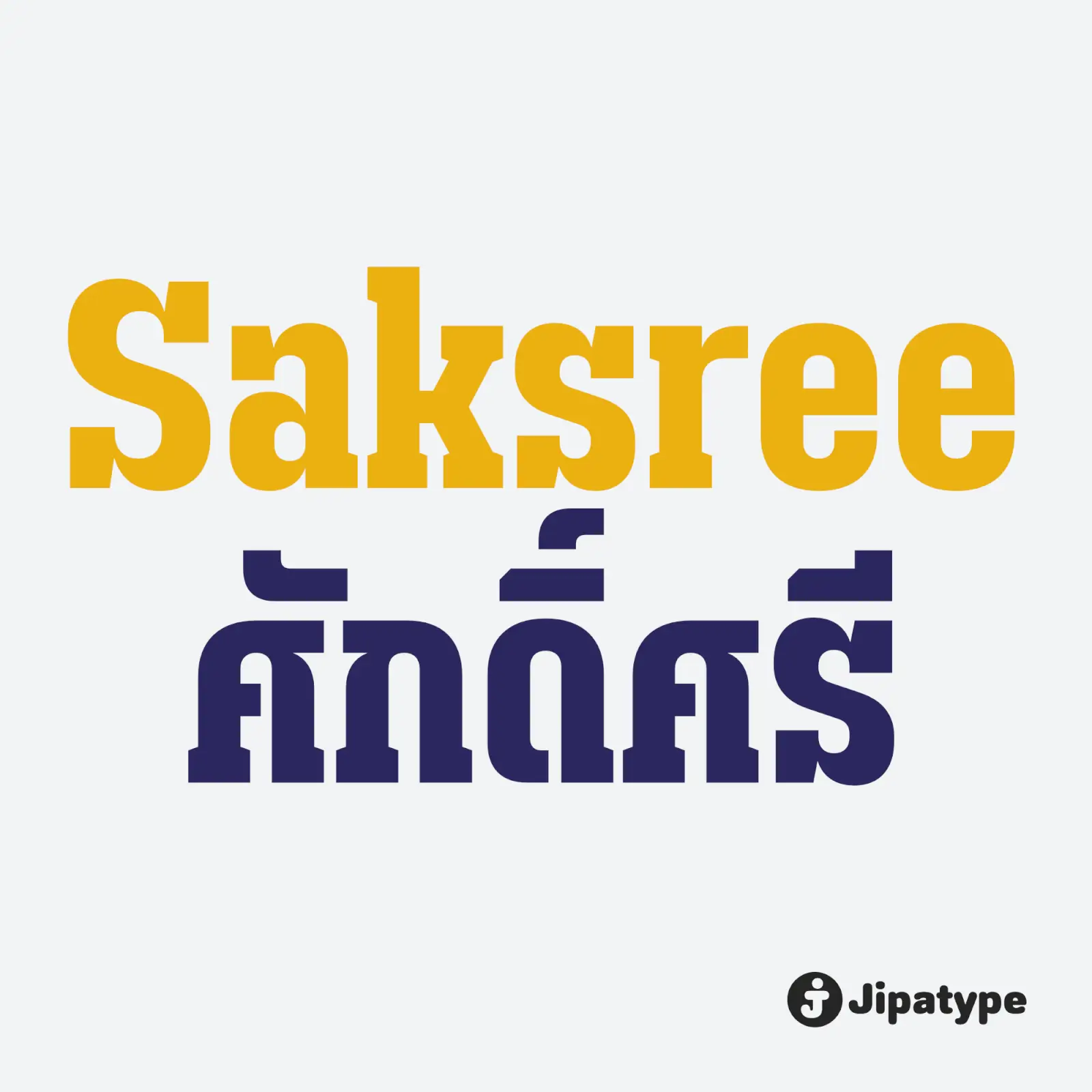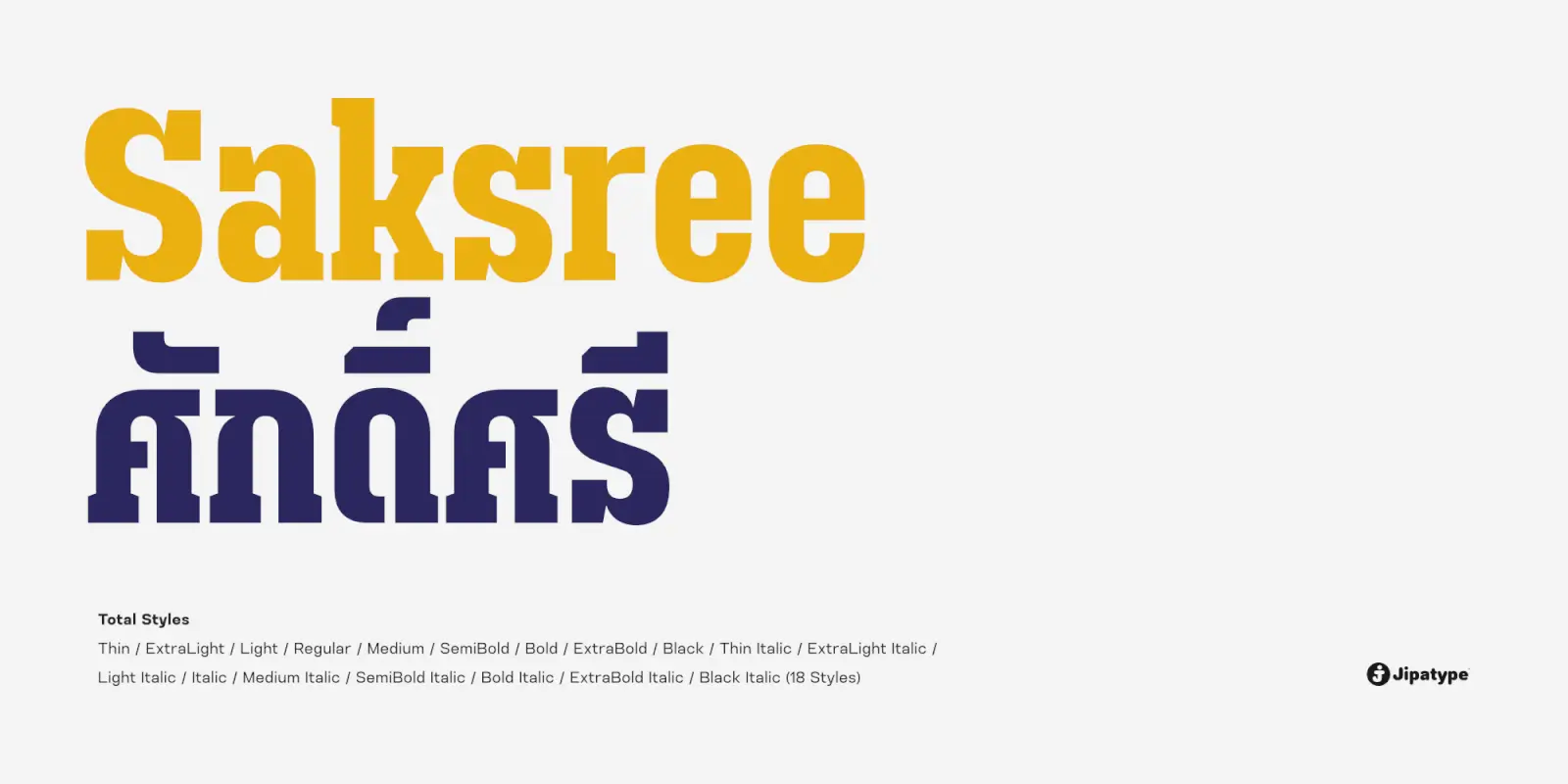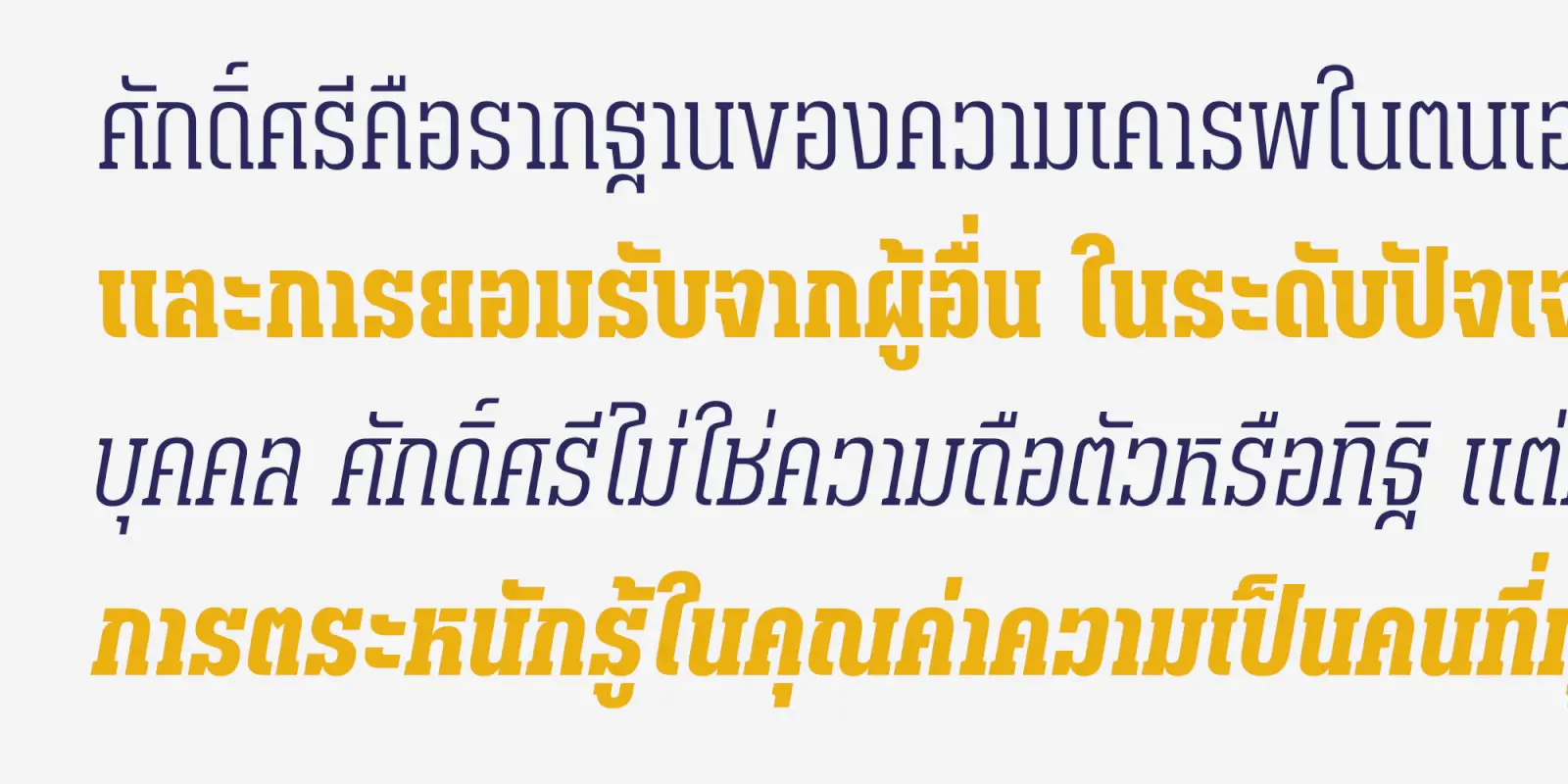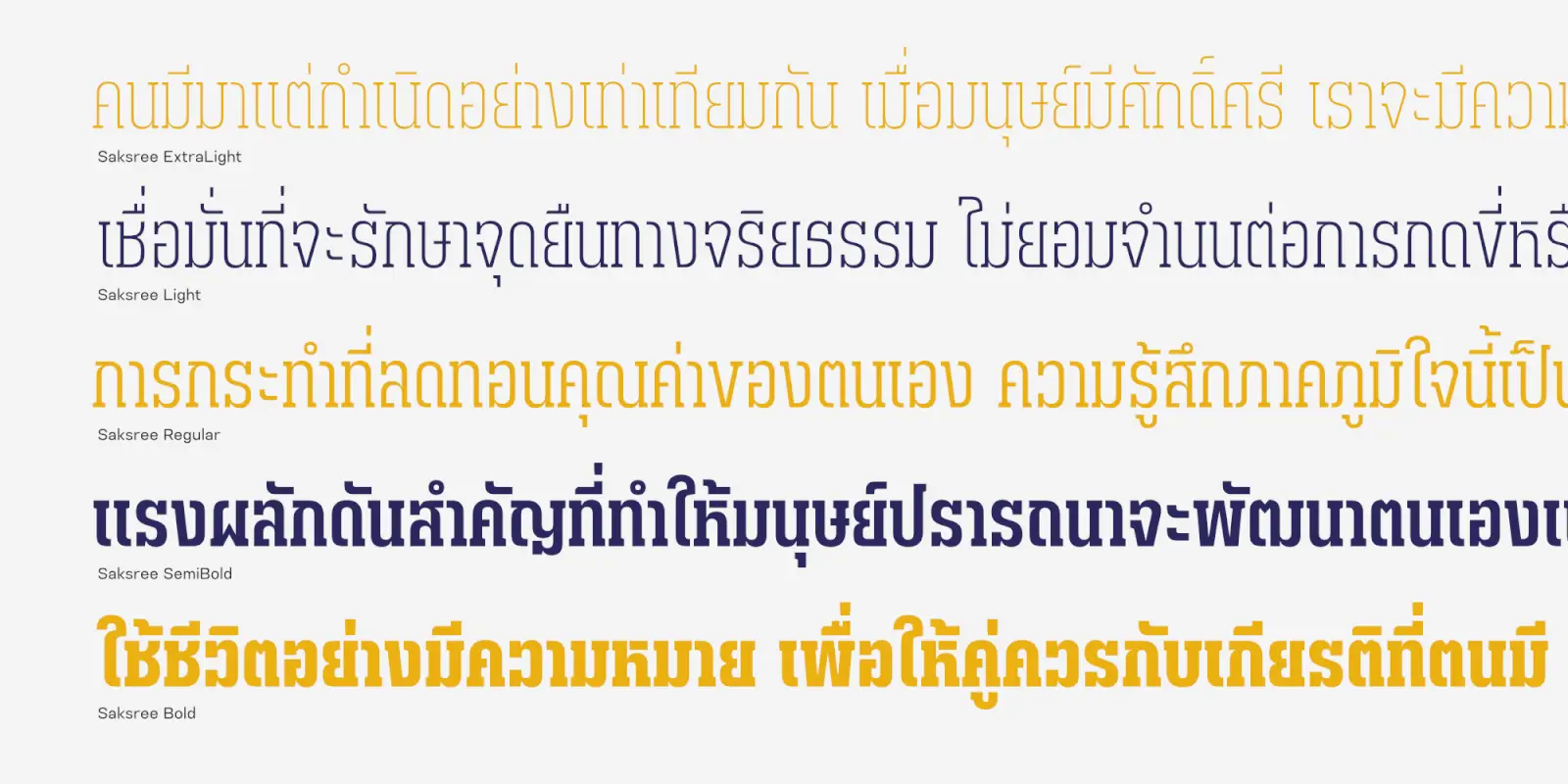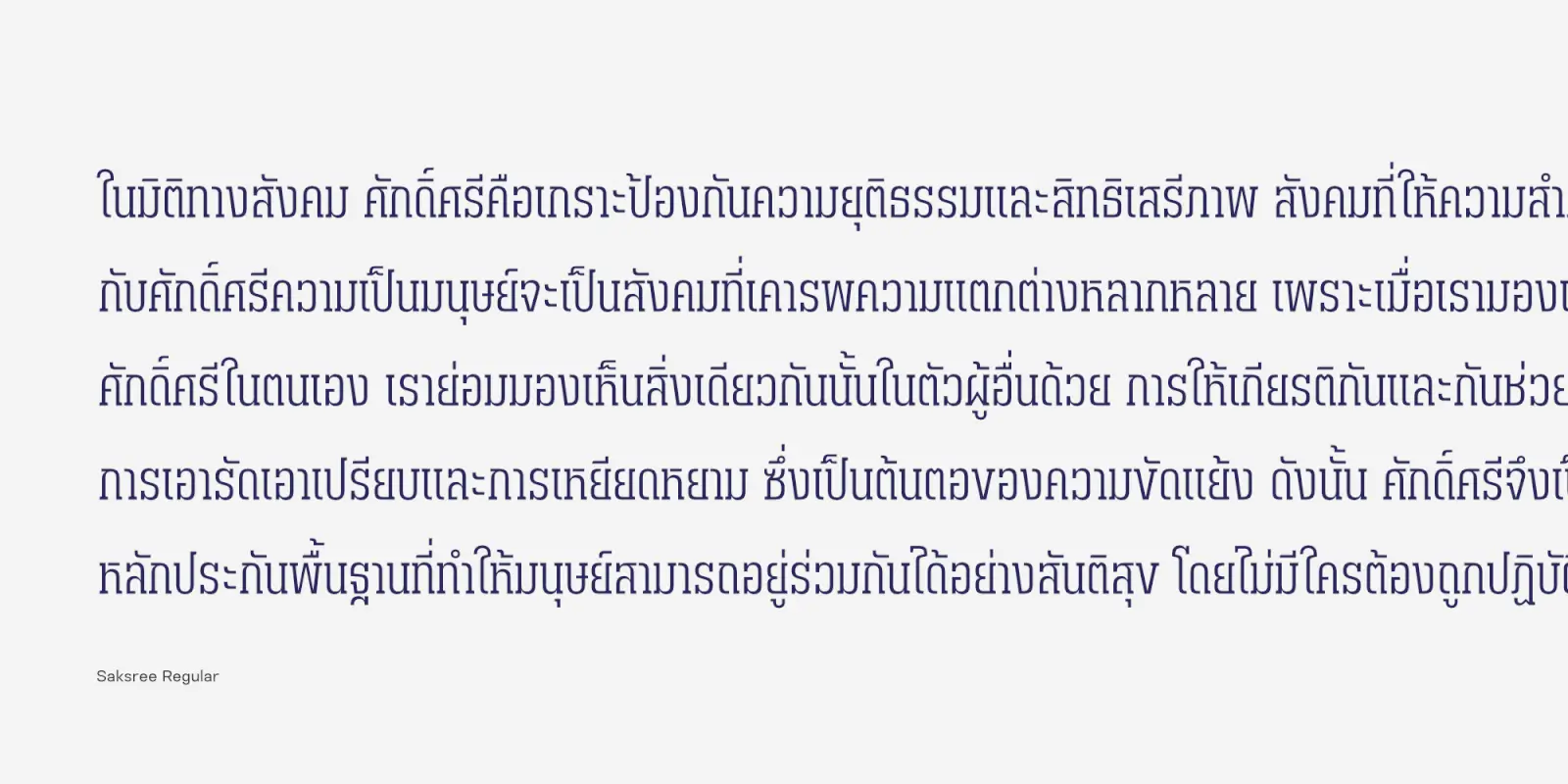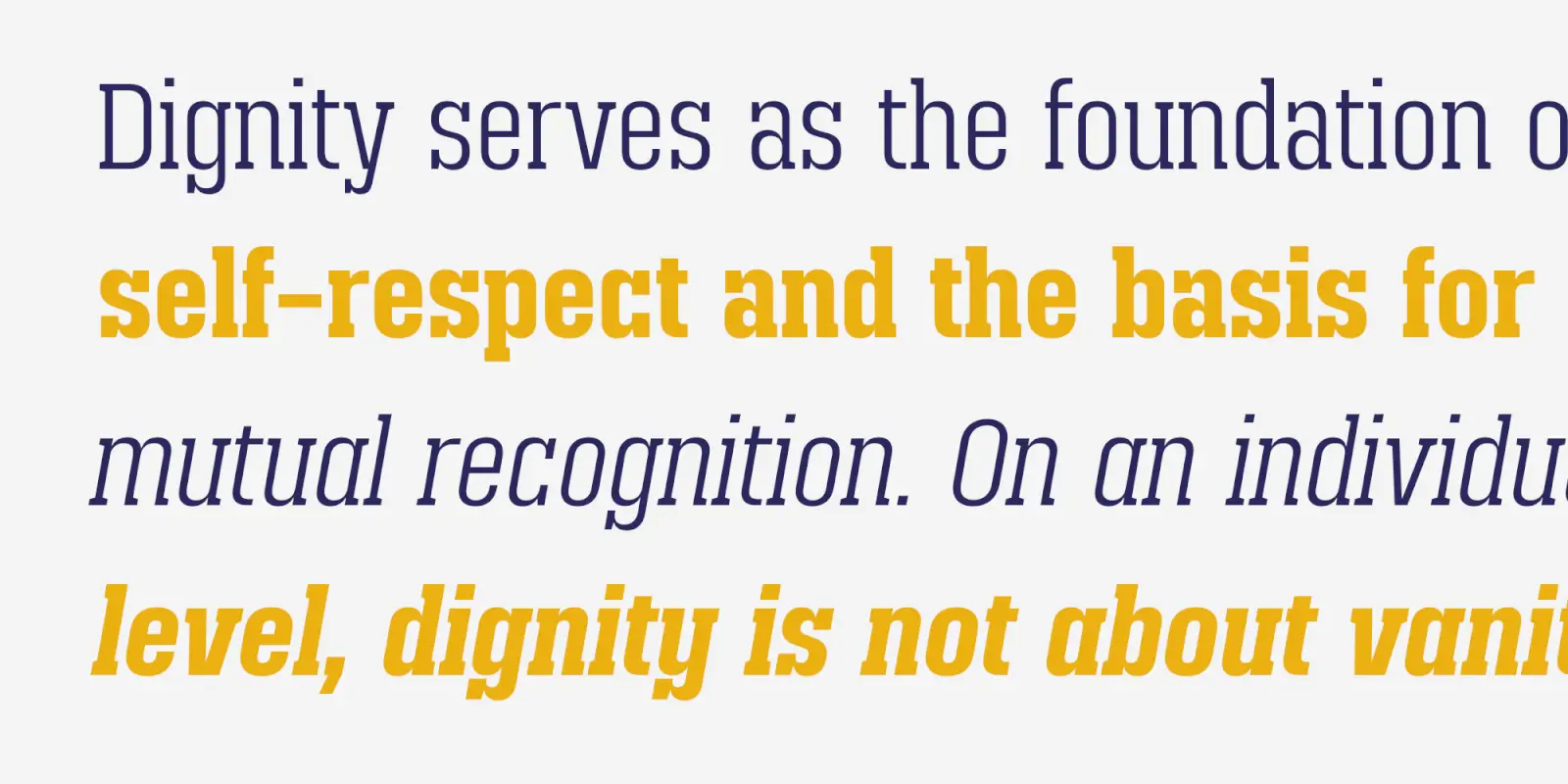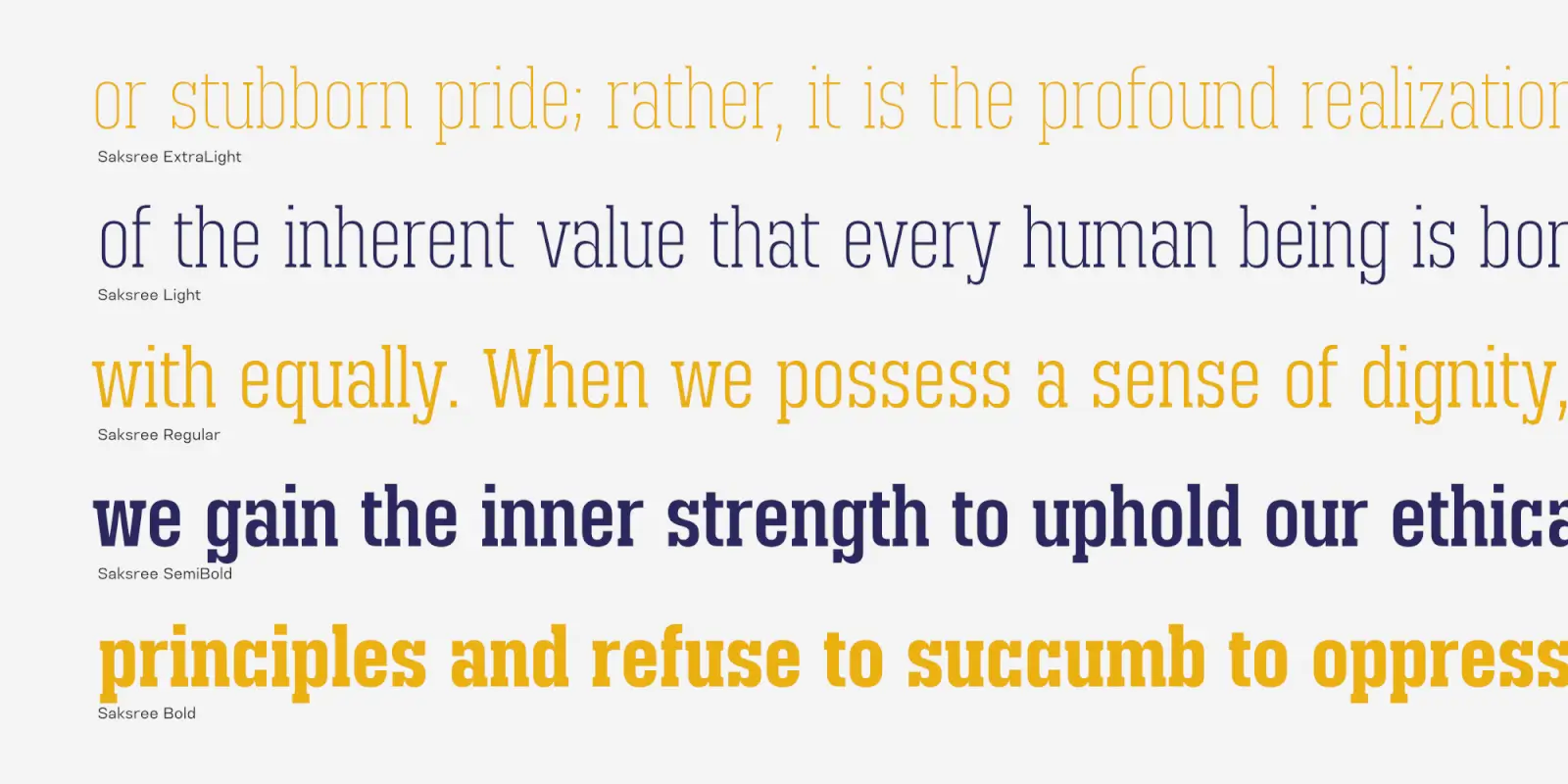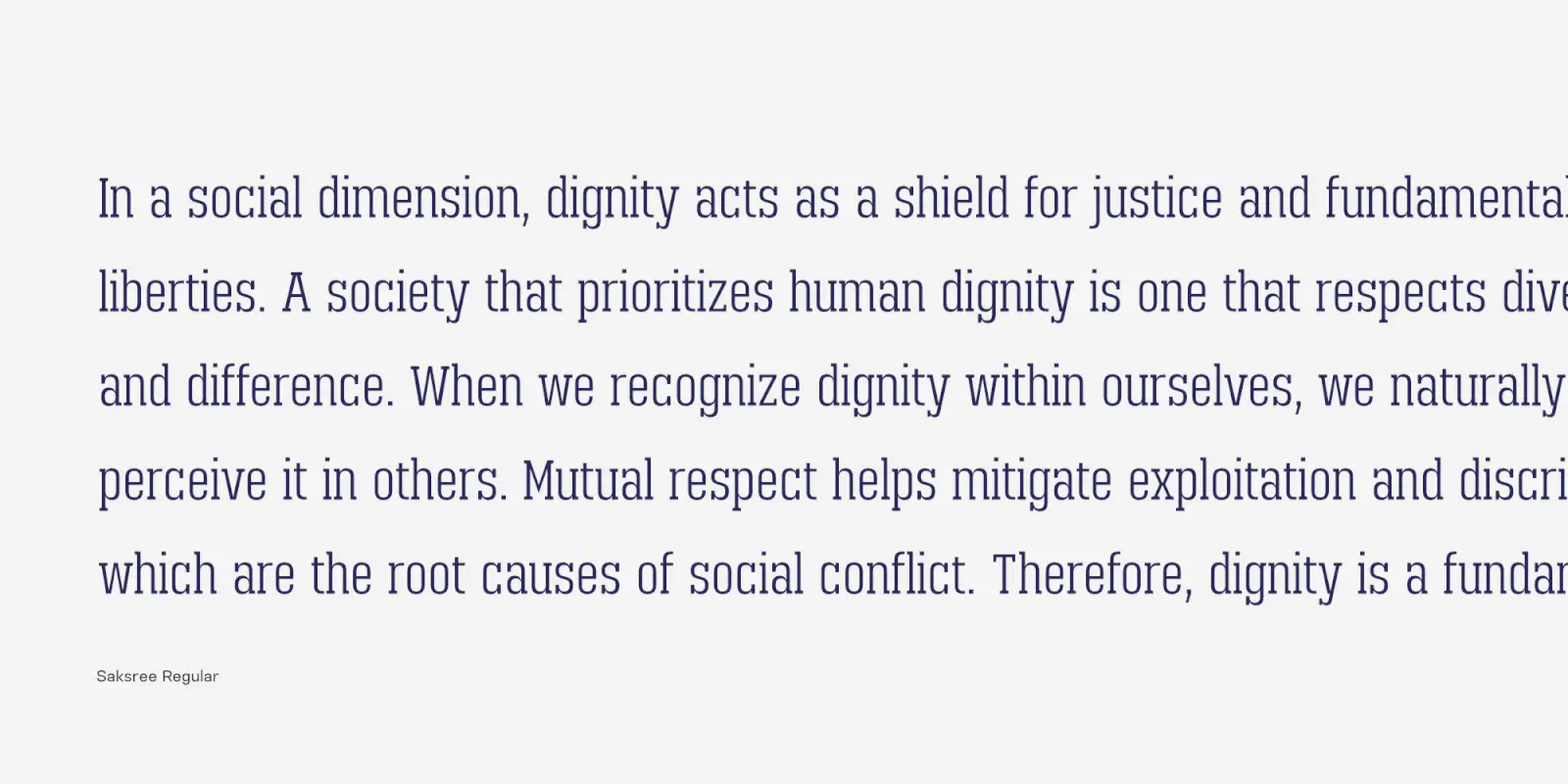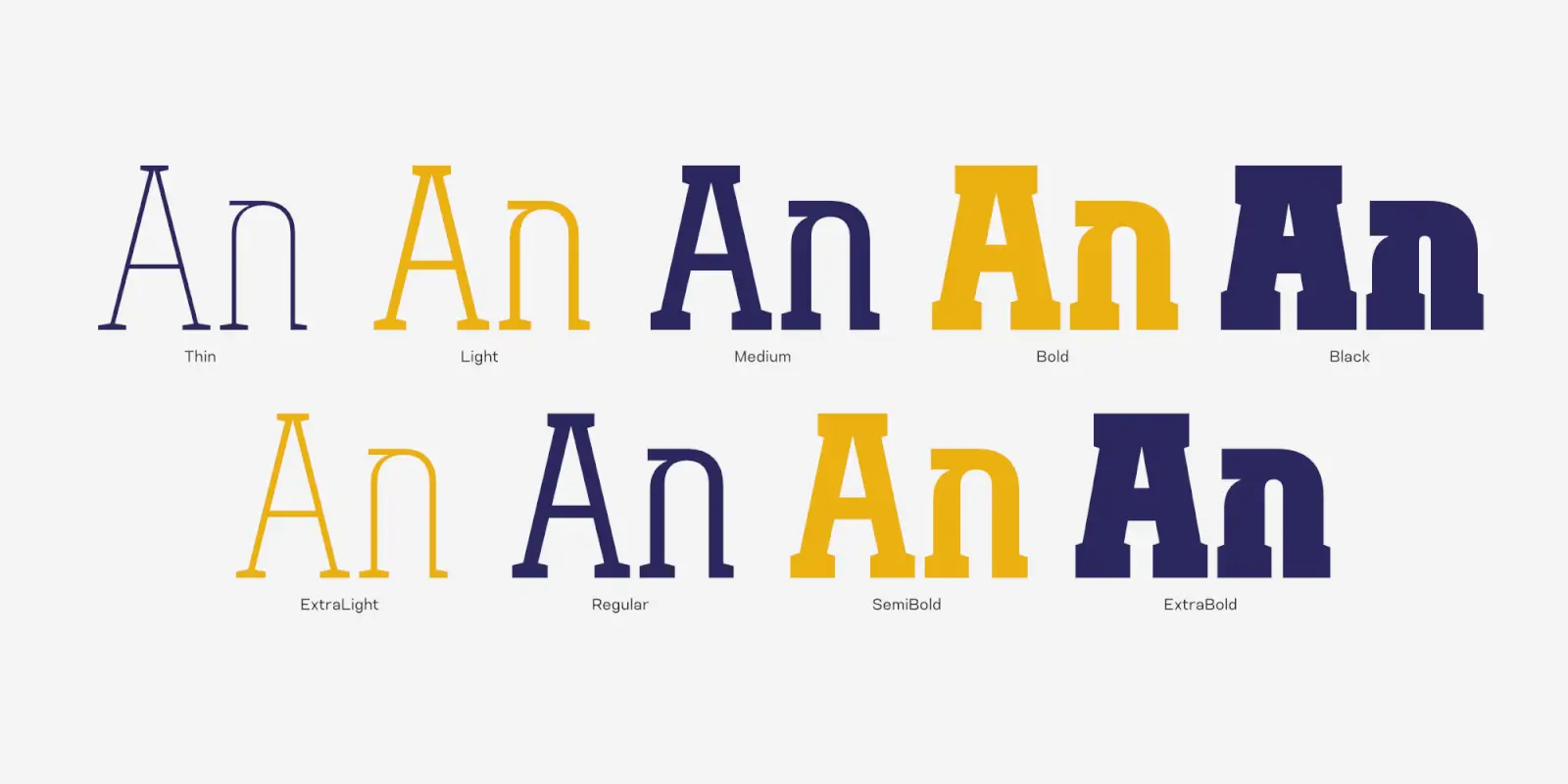
Saksree คือแบบอักษรตระกูล Slab Serif ร่วมที่เปี่ยมไปด้วยบุคลิกอันสุขุมและทรงพลัง โดยเน้นโครงสร้างเส้นสายที่มีความหนาสม่ำเสมอ เพื่อมอบภาพลักษณ์ที่ดูมั่นคง เป็นระเบียบ
ความโดดเด่นของ Saksree อยู่ที่ Serif ทรงเหลี่ยมอันเป็นรากฐานที่มั่นคง ซึ่งช่วยสร้างความรู้สึกที่ดูจริงจังและน่าเชื่อถือให้กับทุกข้อความที่นำเสนอ อีกทั้งยังมีสัดส่วนโครงสร้างที่ค่อนข้างผอมสูง ซึ่งช่วยเสริมสร้างบุคลิกที่ดูสง่างาม ภูมิฐาน และช่วยประหยัดพื้นที่ในการจัดวางพาดหัวได้เป็นอย่างดี
ด้วยทางเลือกที่ครอบคลุมถึง 18 สไตล์ ตั้งแต่ความบาง Thin ไปจนถึงความหนาหนักแน่น Black พร้อมตัวเอียงเข้าคู่กัน ทำให้ Saksree เป็นเครื่องมือที่ยืดหยุ่นสำหรับนักออกแบบในทุกมิติ
ออกแบบโดย : อานุภาพ ใจชำนาญ (Anupap Jaichumnan)